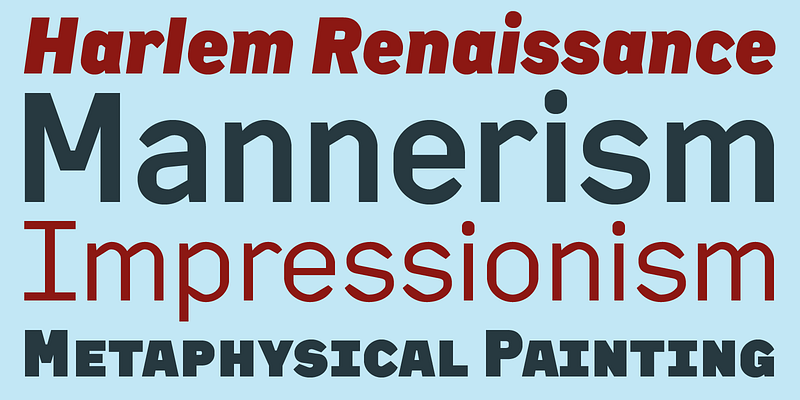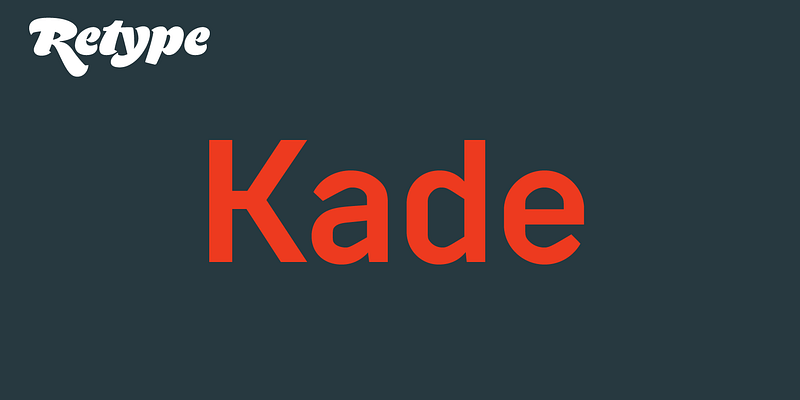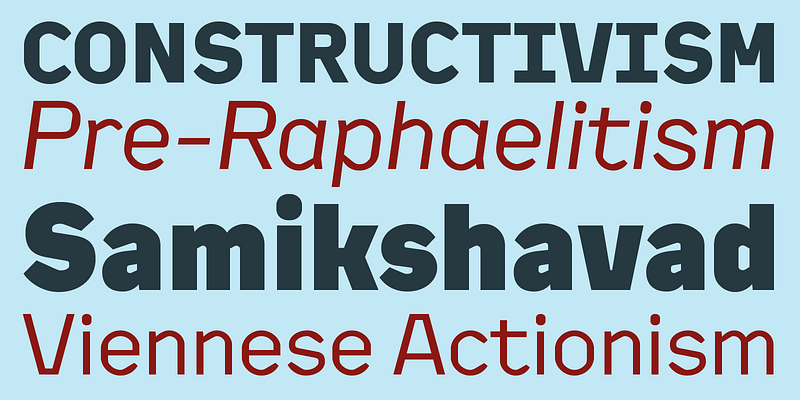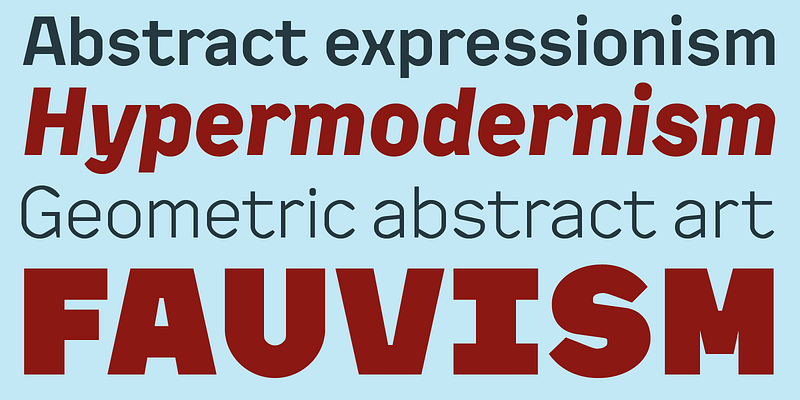
Kade est une famille de polices sans empattement d’affichage et de semi-affichage, basée sur des lettres vernaculaires photographiées au cours des dix dernières années dans et autour des ports d’Amsterdam et de Rotterdam.